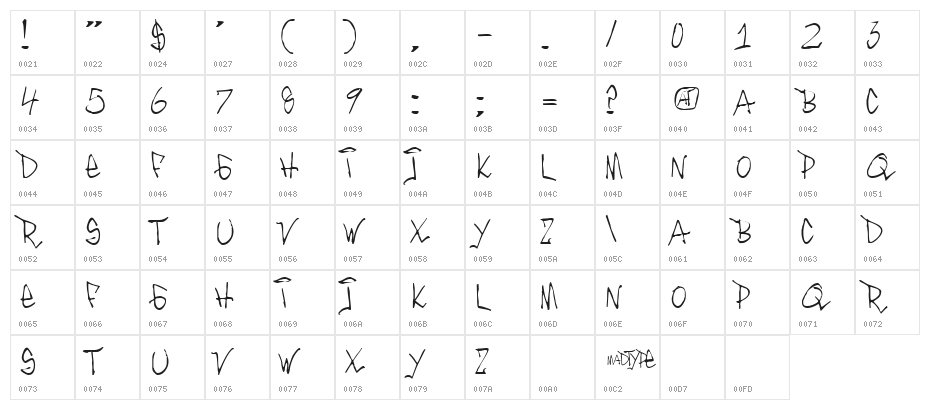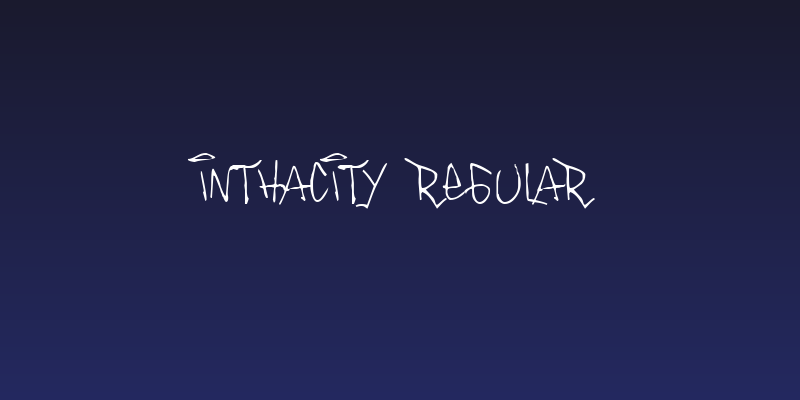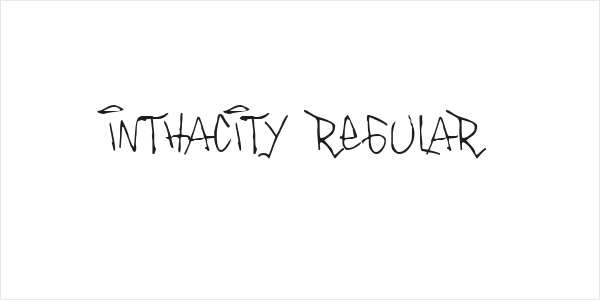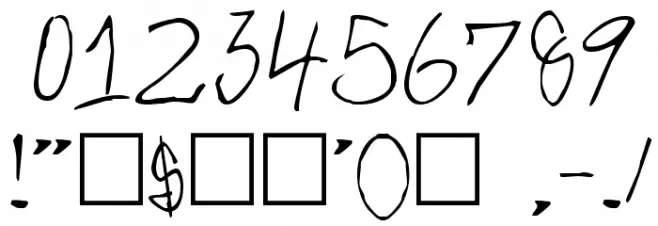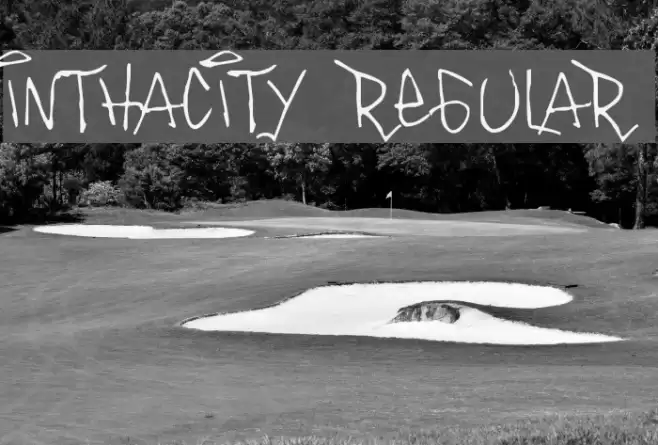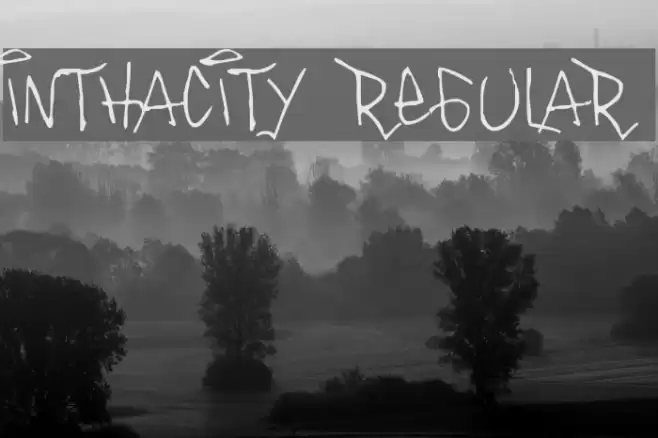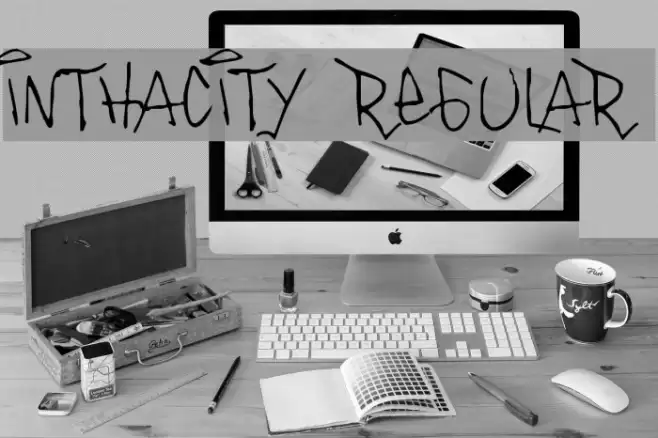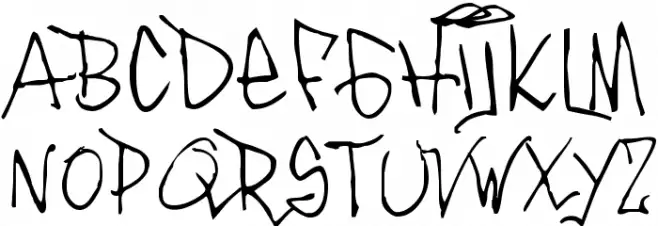
Inthacity Regular Font
| Nom | Inthacity Regular |
| Catégories | Quirky |
| Style général | Urban, Graffiti, Energetic |
| Cas d'utilisation | Logos, Posters, Album Covers |
| Projets proposés | Ideal for street art designs, urban-themed posters, edgy branding, and music album covers. |